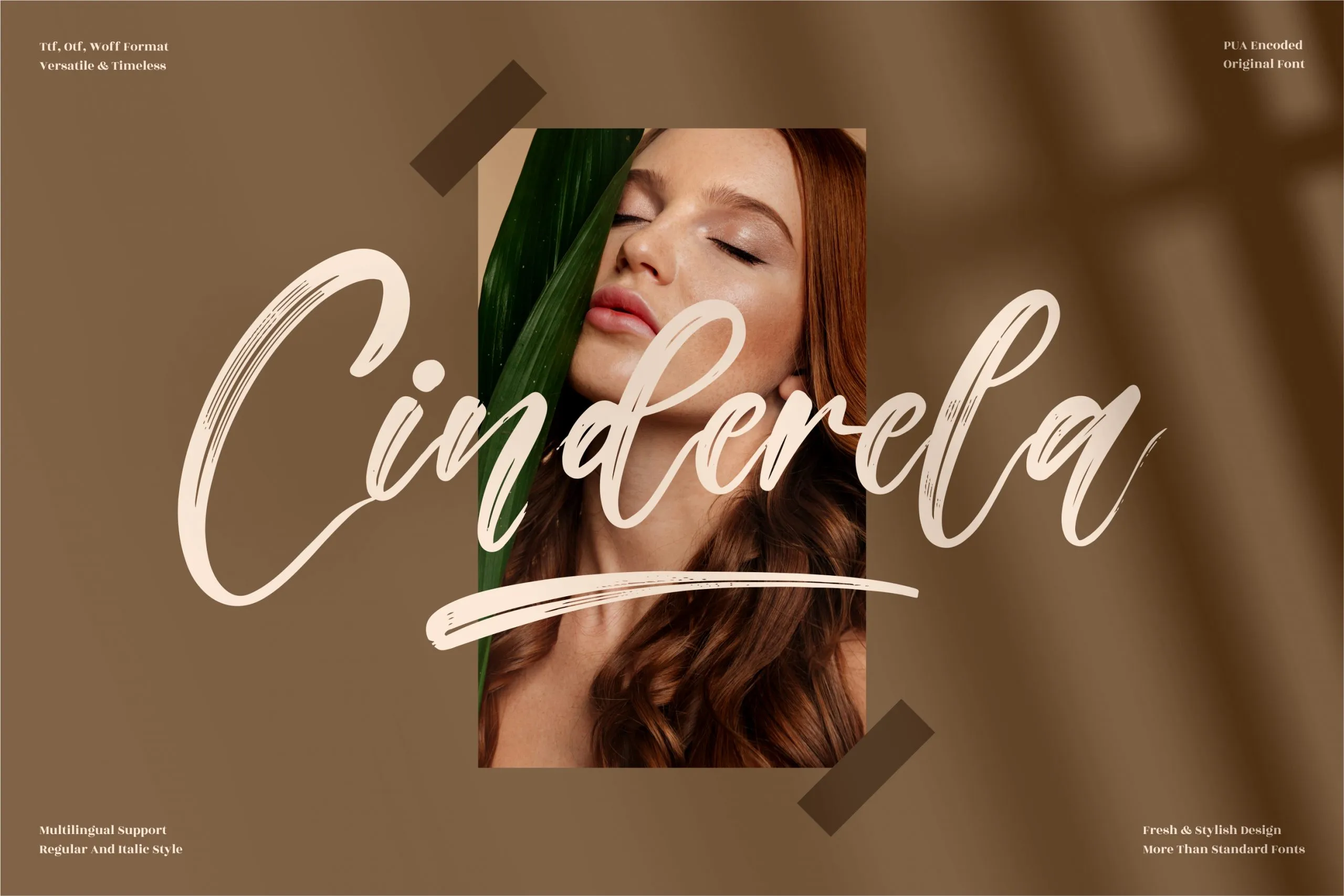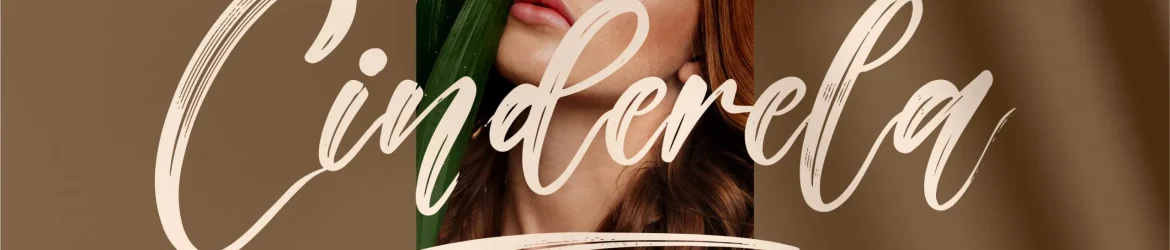
Cinderela Font – Download Grátis
A Cinderela Font é uma fonte escrita à mão perfeitamente adaptada para diversas categorias, incluindo logomarcas, projetos de marca, designs de mobília, embalagens de produtos, xícaras, citações, panfletos, sacolas de compras, camisetas, capas de livros, cartões de nome, cartões de convite, cartazes, etiquetas, fotografia e até mesmo marcas. Seu designer perspectype criou uma fonte única para todos os seus projetos que necessitam de um toque de escrita à mão, seja em eventos especiais ou como parte de qualquer projeto de luxo onde se deseja deixar sua marca personalizada com a elegância e autenticidade da escrita à mão. Compreender o valor dessa fonte não apenas é adquirir uma ferramenta de design versátil, mas também participar na criação de um design que transmite emoções e história através do papel impresso ou digital.